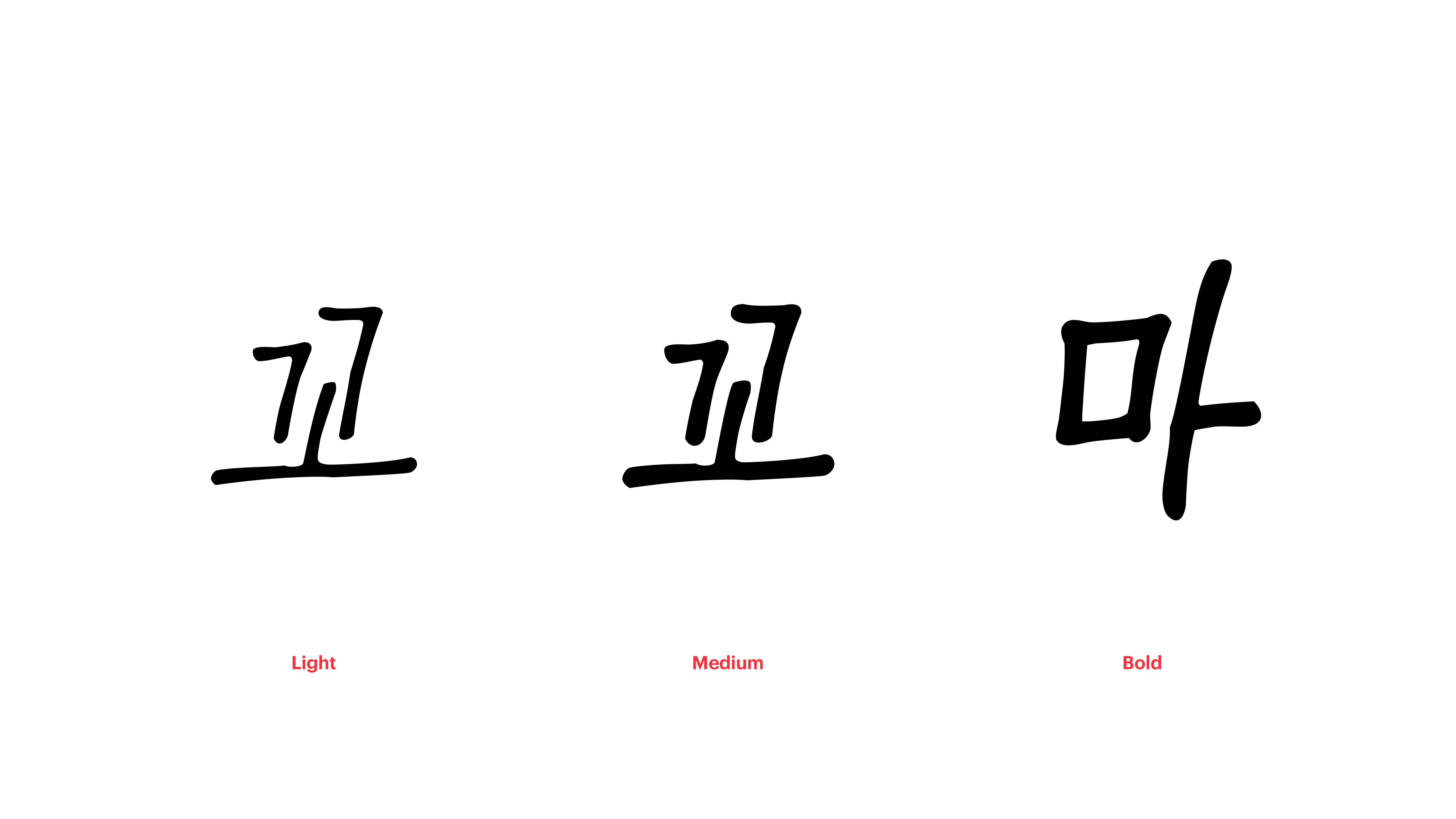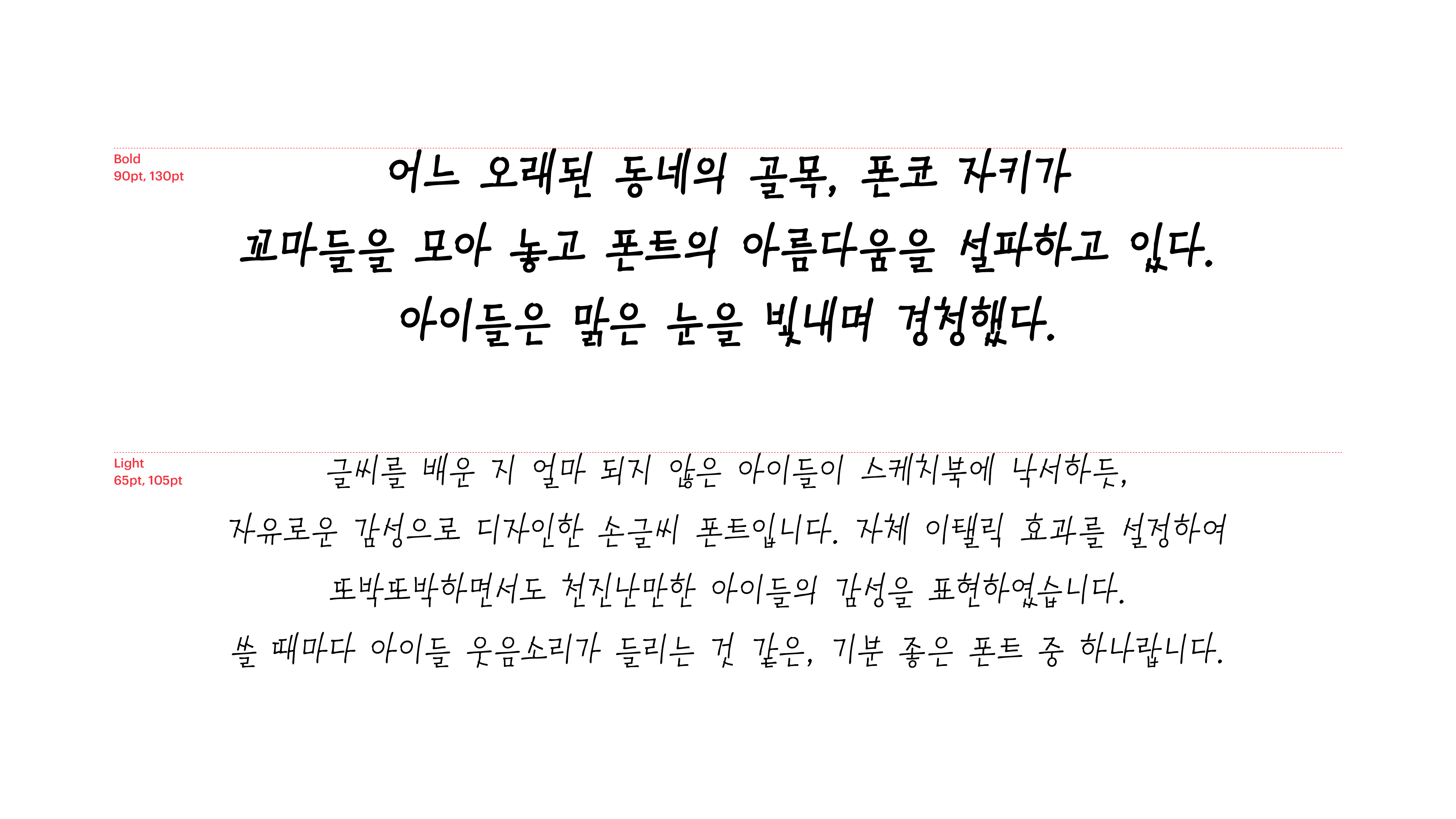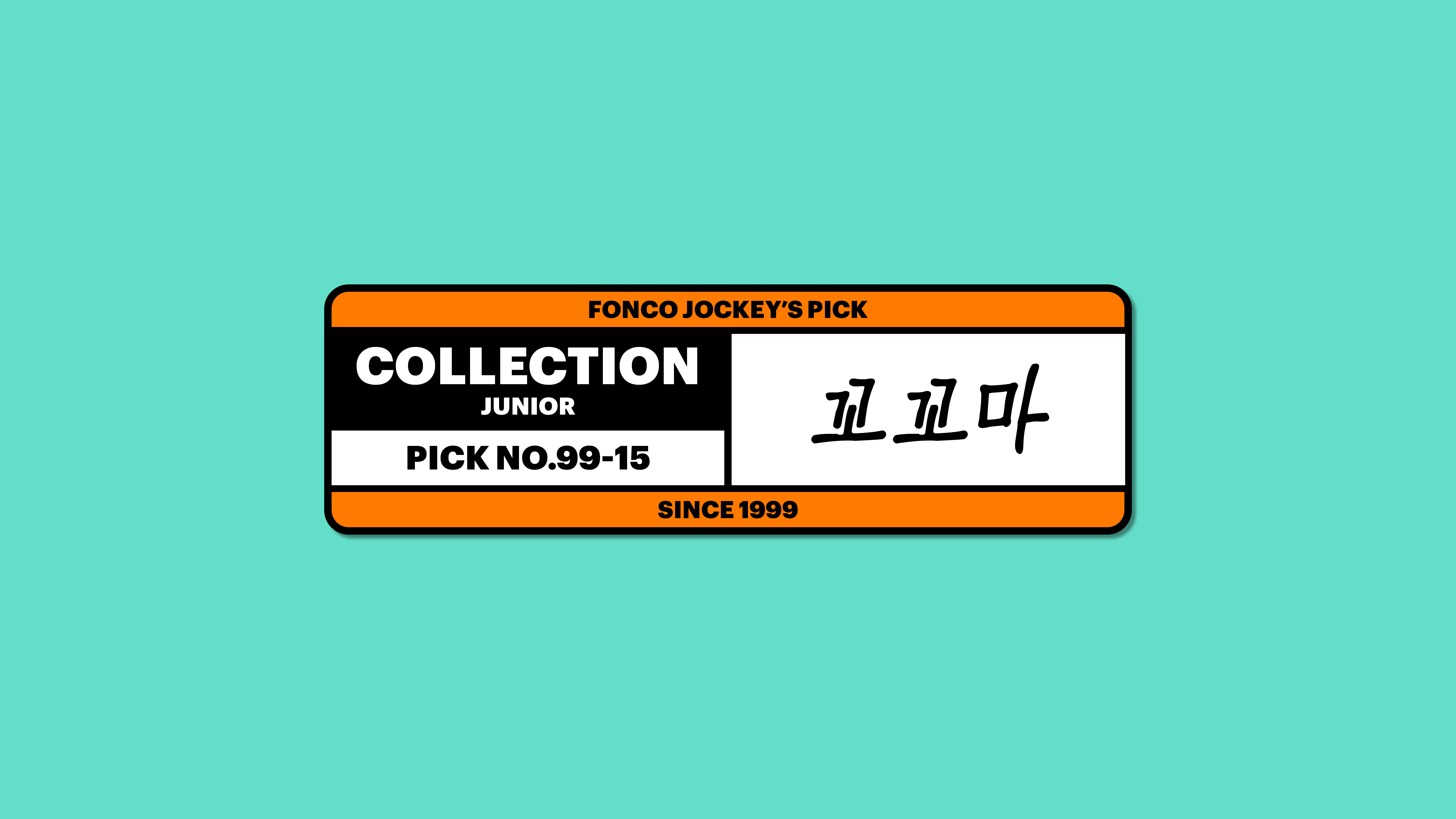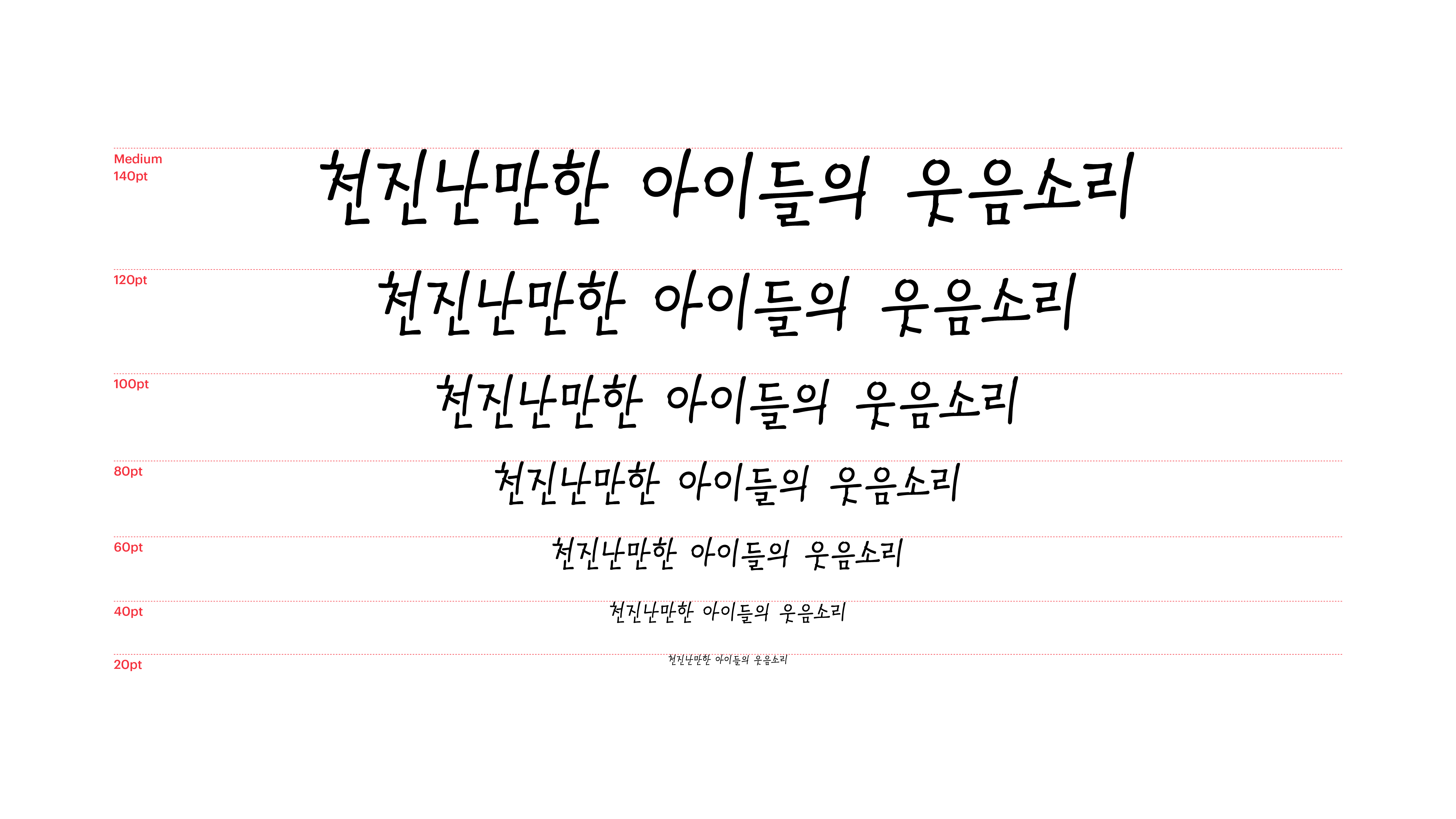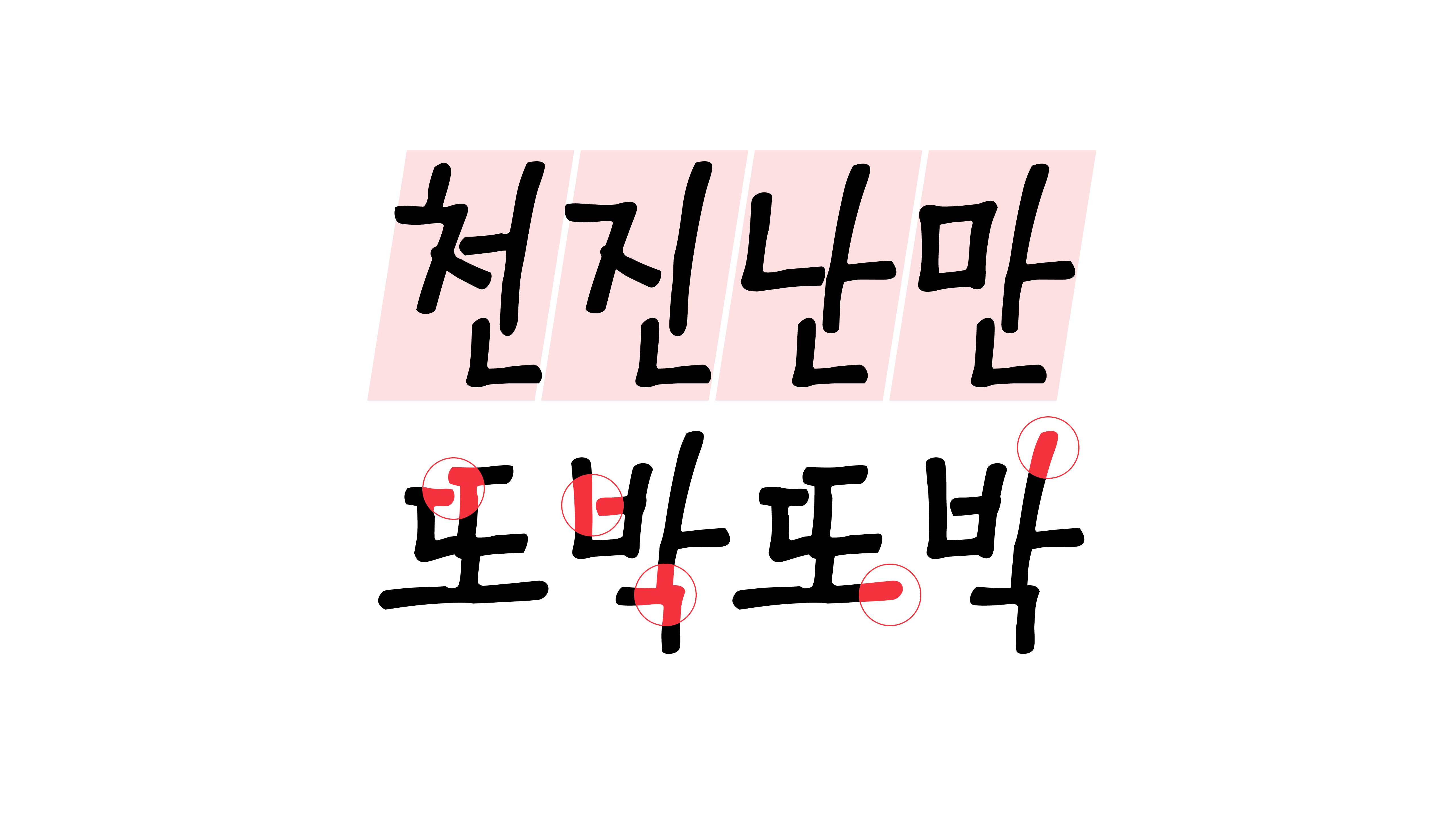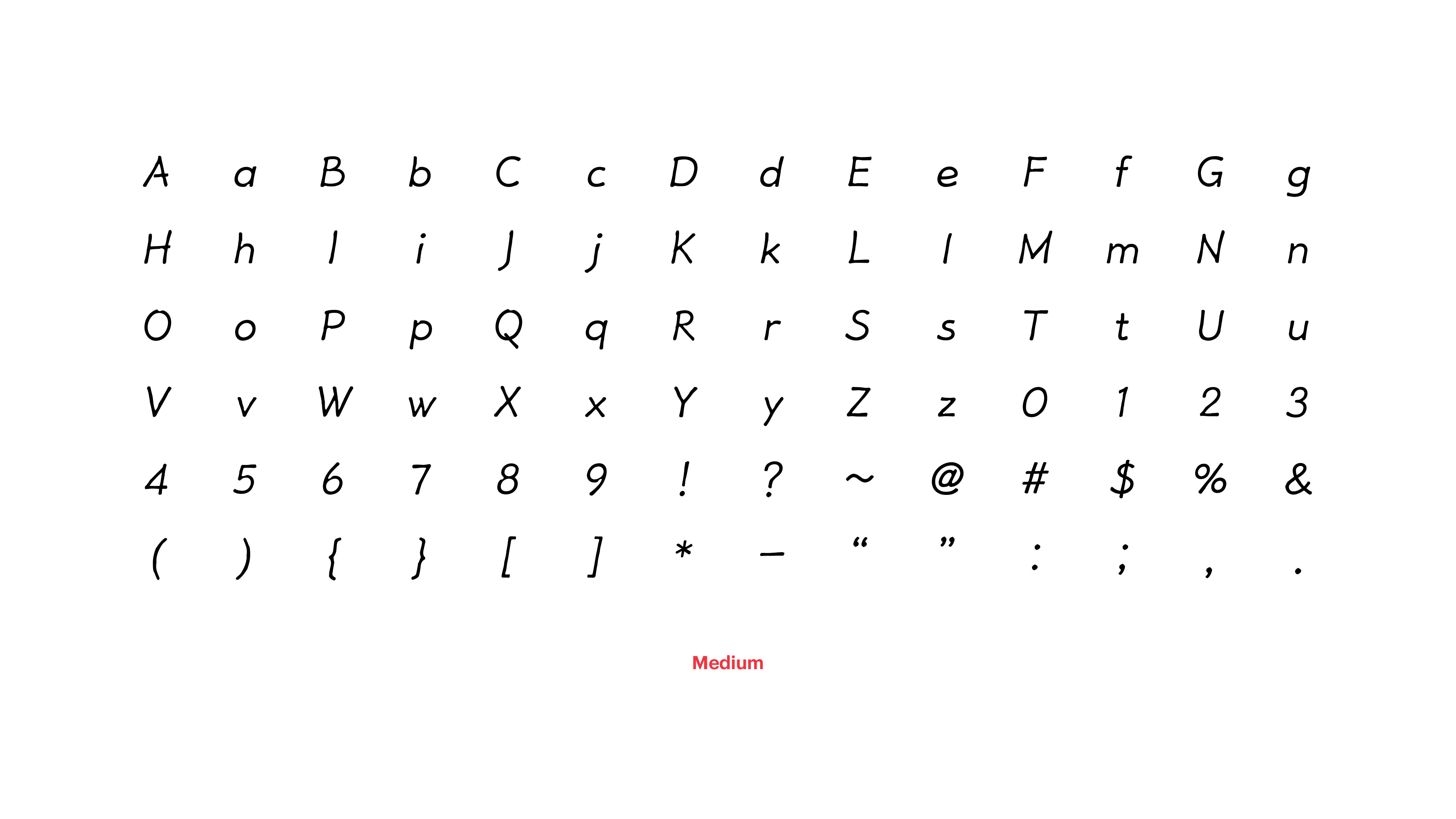
꼬꼬마
Yoon 꼬꼬마
글씨를 배운 지 얼마 되지 않은 아이들이 스케치북에 낙서하듯, 자유로운 감성으로 디자인한 손글씨 폰트입니다. 자체 이탤릭 효과를 설정하여 또박또박하면서도 천진난만한 아이들의 감성을 표현하였습니다. 쓸 때마다 아이들 웃음소리가 들리는 것 같은, 기분 좋은 폰트 중 하나랍니다.